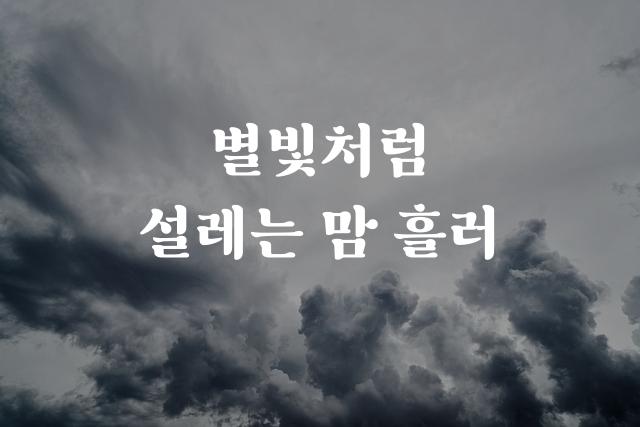
레몬빙수는 눈서리 제작사에서 만든 네모난 형태의 독특한 폰트입니다. 장식체 감성을 품고 있어 캐주얼하면서도 감각적인 디자인을 선사합니다.
레몬빙수은(는)
장식 스타일, 네모꼴, 단단함, 별모양/패턴 계열의 생김새를 가지고 있으며
초대장, 인사말 카드, 카페 메뉴 등에서 자주 활용되며, 효과적인 메시지 전달에 적합합니다.
이 폰트는 음식/식음료, 라이프스타일, 이벤트/웨딩 분야에 잘 어울리며,
친근한, 귀여운, 재미있는 느낌을 담고 있는 것이 특징입니다.